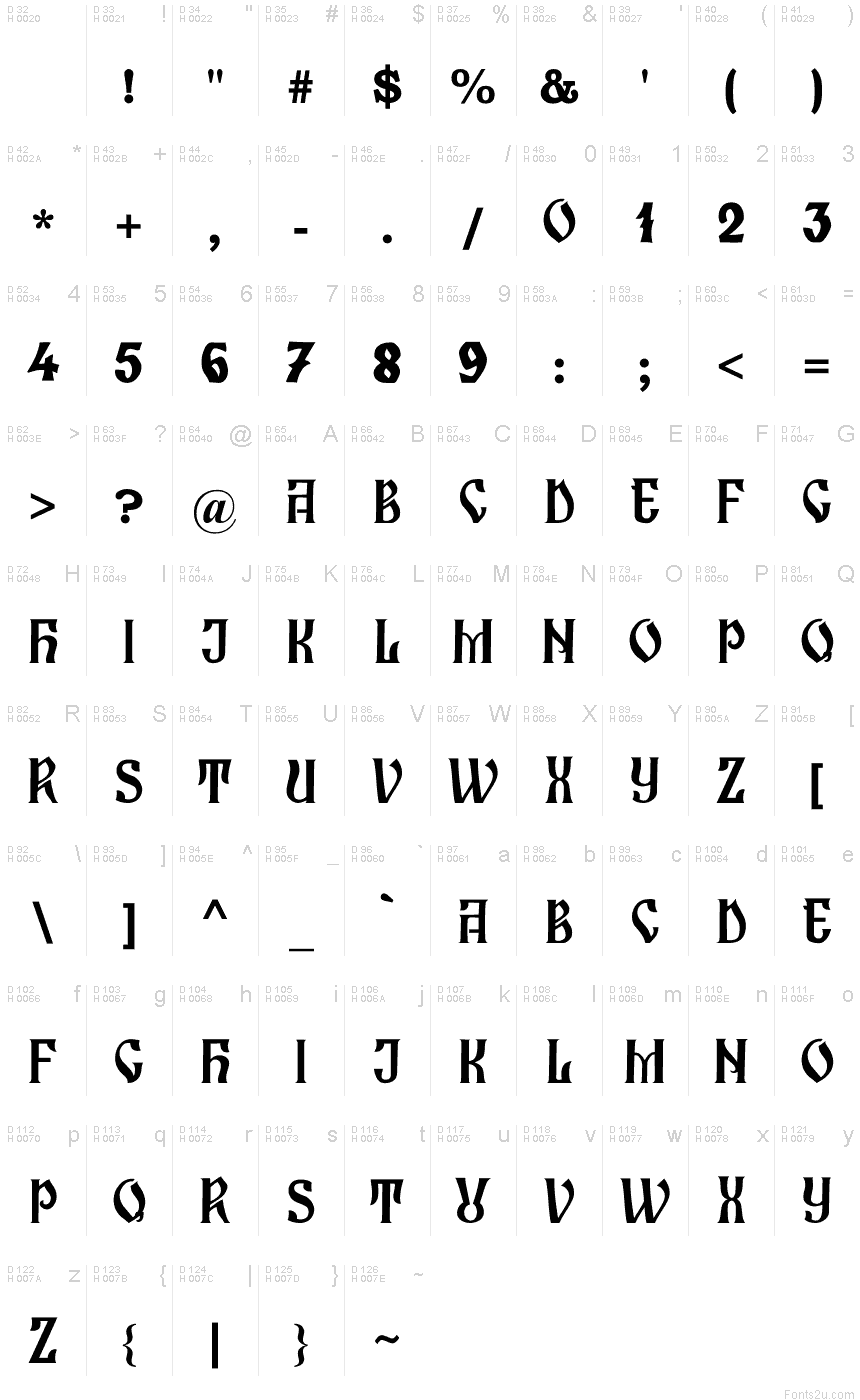
Zamolxis I to darmowy gotycki font typu display z wyraźnie średniowiecznym klimatem rzeźbionych liter. Litery łączą ciężki wertykalny rytm z ostrymi klinami, rozdzielonymi krzywiznami i wewnętrznymi cięciami. Sprawia to, że formy wydają się ceremonialne, a nie tylko przestarzałe, z obłymi znakami przechodzącymi w spiczaste, niemal heraldyczne kształty.
Naturalnie pasuje do plakatów, okładek książek, brandingu fantasy, grafik zespołów muzycznych, plansz tytułowych i otwarć rozdziałów, gdzie potrzebujesz darmowego fontu, który szybko buduje atmosferę. Użyj go do krótkich nagłówków, monogramów lub inicjałów, ponieważ dramatyczny kontrast między tępą masą a nacięciami przypominającymi ostrza sprawia, że nawet kilka liter zyskuje wygląd godła.